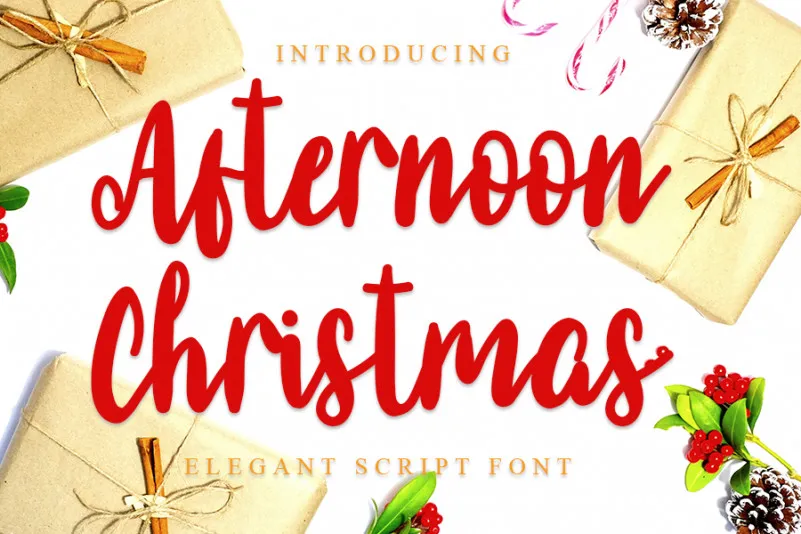
Afternoon Christmas Script Font – Download Grátis
A Afternoon Christmas Script Font é uma fonte criada pelo designer freshtypeink, com traços amigáveis e frescos, ricos e elegantes. Ela oferece um toque de serenidade perfeito para aqueles momentos de confraternização natalina, especialmente adequada para cartões de aniversário ou recados especiais durante o período festivo. Além disso, é uma escolha perfeita para qualquer projeto de decoração pessoal que seja exigente em termos de romantismo e sofisticação. Esta fonte pode tornar seu próximo trabalho de arte ainda mais especial, adicionando um toque mágico à sua criação. Seja você decorando as árvores de natal ou criando cartões de aniversário, esta Afternoon Christmas Script Font certamente enriquecerá suas obras de arte e fará uma excelente impressão em qualquer ocasião especial.